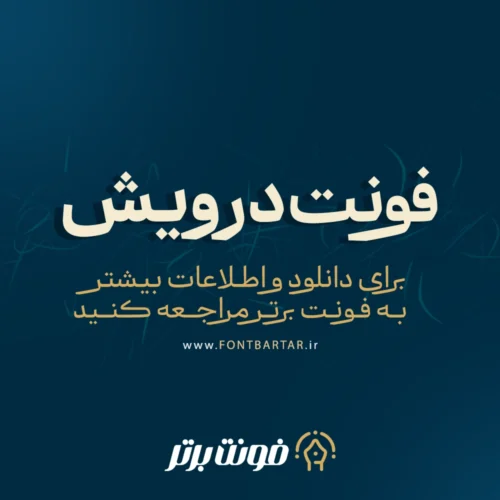
فونت فارسی درویش
فونت درویش ترکیبی از خطوط ریحان و نسخ است که به منظور بهبود خوانایی، ویژگیهای آنها با هم تلفیق شده است. در فونت فارسی درویش، خطوط کشیده و بلند ریحان برای افزایش وضوح کوتاهتر شدهاند، دانلود فونت درویش در حالی که دیگر حروف در مقایسه با نسخ، عریض تر طراحی شدهاند.
تمرکز اصلی طراحی فونت تایپوگرافی درویش بر خوانایی بهتر و جذابیت بصری بوده است، بدون توجه به محدودیتهای طول و عرض متن. این توجه ویژه به خوانایی و توازن زیباشناختی باعث شد که فونت درویش موفق به کسب جایزه معتبر تایپوگرافی از Type Directors Club (TDC) شود.
- زبانهای پشتیبانی شده در فونت درویش: فارسی , عربی , کوردی
- وزن | استایل : 8 وزن، 2 سبک
- اعداد فارسی: دارد
- وریبل فونت: فونتهای متغیر دارای محور: تغییر وزن